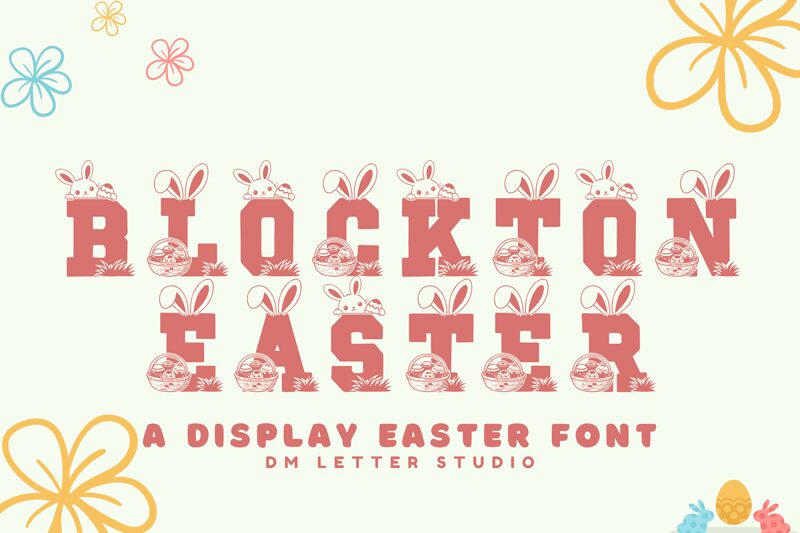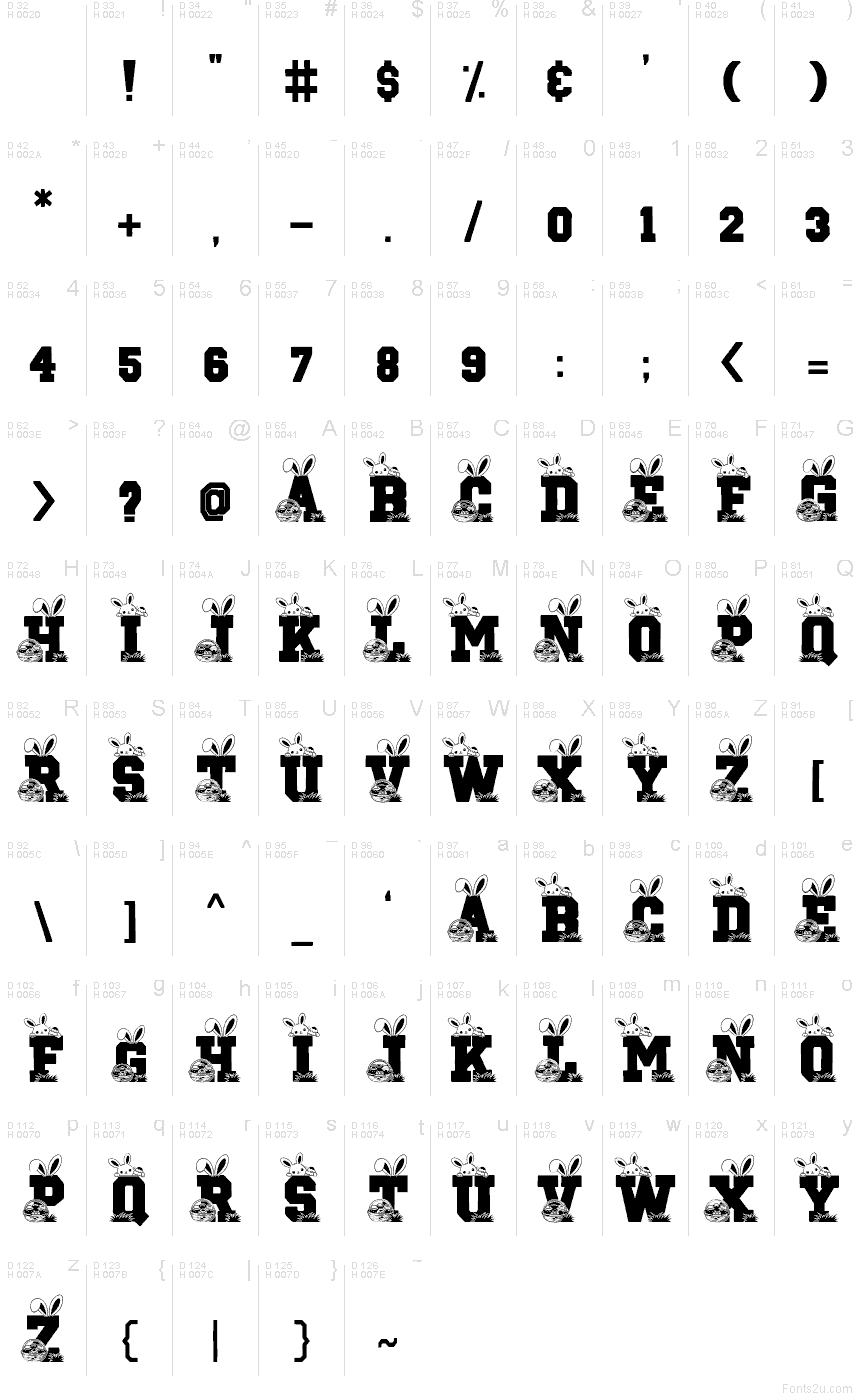
Blockton Easter
A Blockton Easter, da Dm Letter Studio, é uma fonte display gratuita para a Páscoa. Apresenta letras robustas e sólidas, decoradas com orelhas de coelho e pequenos detalhes festivos, como ovos e grama. O estilo é artesanal e festivo, com cada caractere ostentando o mesmo motivo sazonal, permitindo que as palavras formem uma peça decorada coesa.
A Blockton Easter funciona perfeitamente em cartões de Páscoa, convites de primavera, faixas de lojas, posts para redes sociais, etiquetas de presente e rotulagem sazonal. Os coelhinhos e ovos incorporados criam um visual temático instantâneo para títulos, embalagens criativas e gráficos promocionais, dispensando a necessidade de adornos extras.